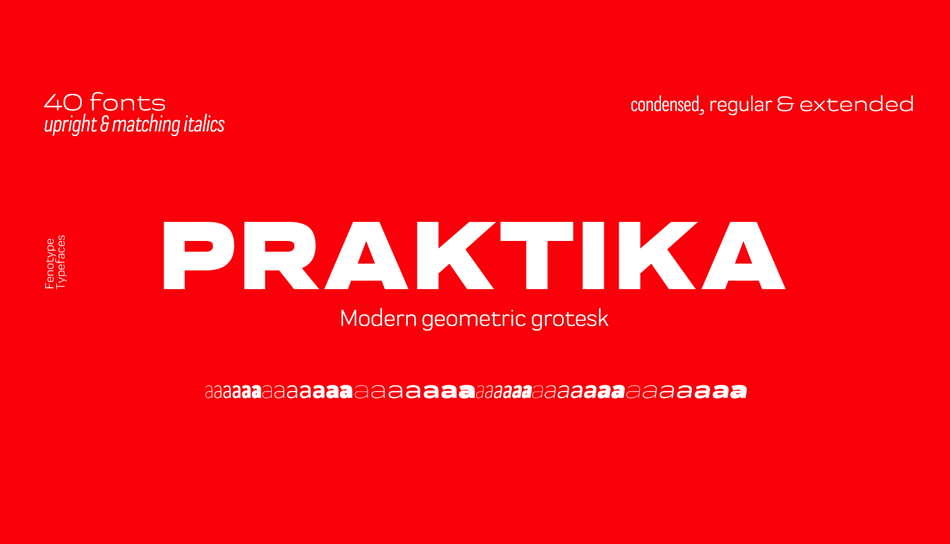
Estou aqui uma fonte que vai revolucionar a maneira como você cria e apresenta seu conteúdo, Praktika Font Family. Este é um conjunto multifuncional de 40 tipos criado por Emil Karl Bertell, publicados pela Fenotype. Perfeito para qualquer aplicação visual, desde o design gráfico até o layout editorial, Praktika oferece três níveis distintos de espessura e traço: extra fino, médio e muito grosso. Conceptualmente, Praktika é uma reinterpretação das estilografias grotescas conhecidas do início do século XX. Inspiradas nas tipografias usadas em placas de trânsito europeia dos anos 1900, Praktika foi reinventada para atender às demandas da sociedade moderna. Com seu design elegante e versátil, é perfeito para qualquer aplicação que você possa imaginar. Seja para criar um layout atraente, desenvolver uma identidade visual única ou simplesmente imprimir um documento pessoal, Praktika tem o traço certo para deixar seu trabalho ainda mais profissional. Através de sua simplicidade e eficiência, Praktika é mais do que apenas uma fonte; ele é uma ferramenta poderosa para transformar qualquer texto em uma obra de arte visual.